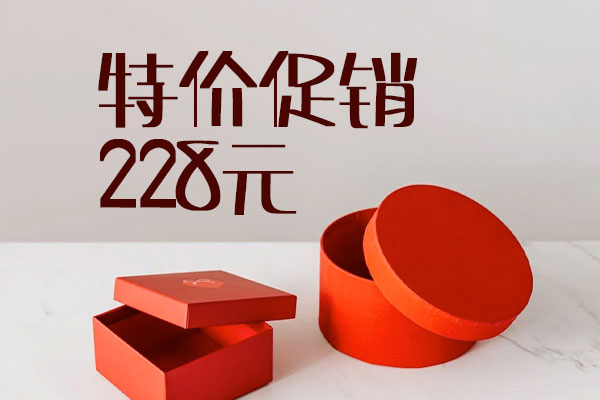
宅在家麦克笔
宅在家麦克笔字体的简体和繁体支持都非常好,已经覆盖了简体国标GB2312的6763个汉字,基本不存在缺字现象。这使得它在实际使用中能够满足各种需求,无论是简体还是繁体中文的书写,都能表现出优美的外观和流畅的书写感。这款字体的创作灵感来自于手写马克笔的独特风格,给人一种轻松愉快的视觉感受,相信会成为许多设计师和文字工作者的好帮手。
宅在家麦克笔效果预览